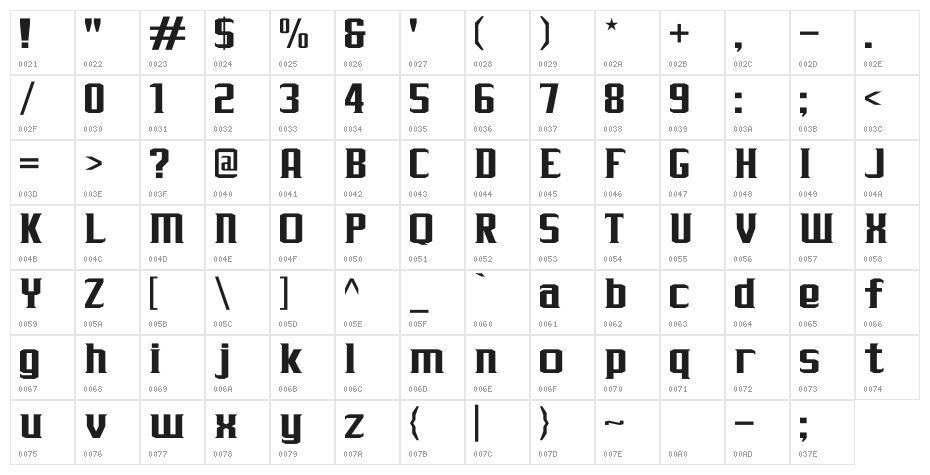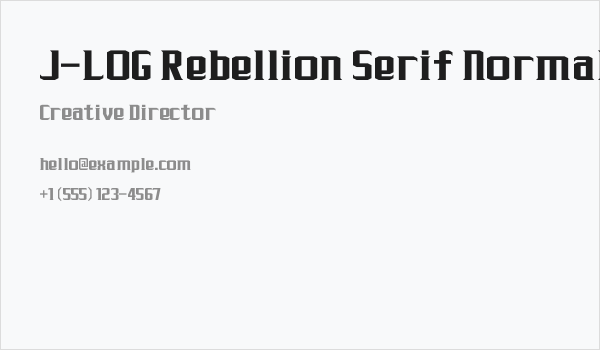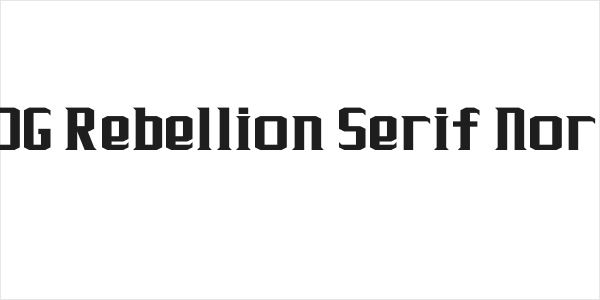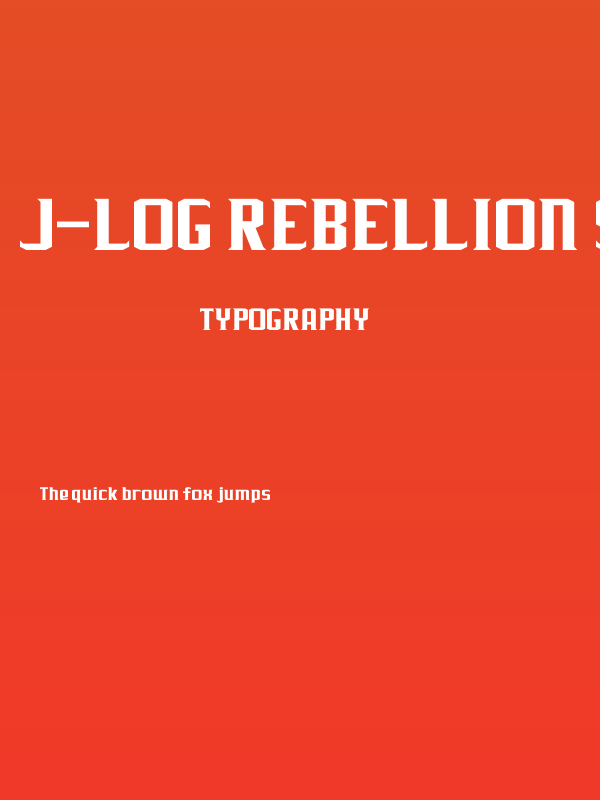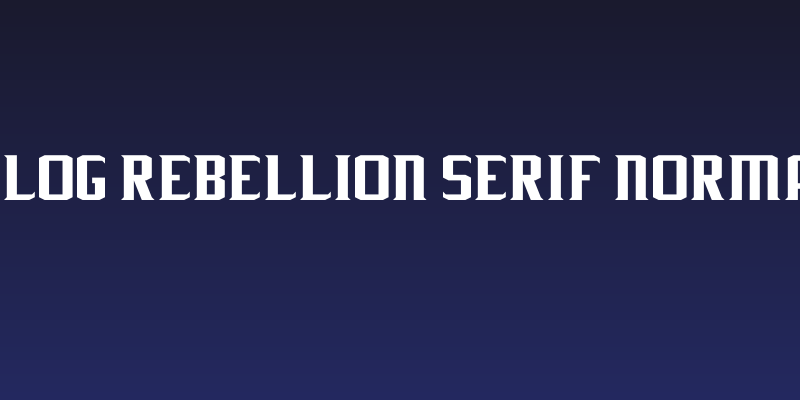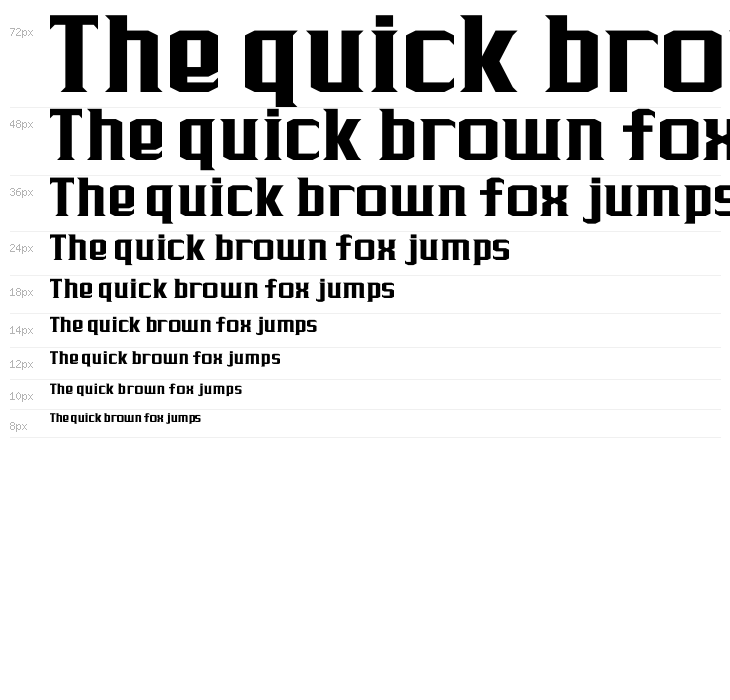
J-LOG Rebellion Serif Normal Font
| Categorie | Serif |
| Progetti proposti | Ideal for branding, headlines, posters, and any design requiring a strong, modern aesthetic. |